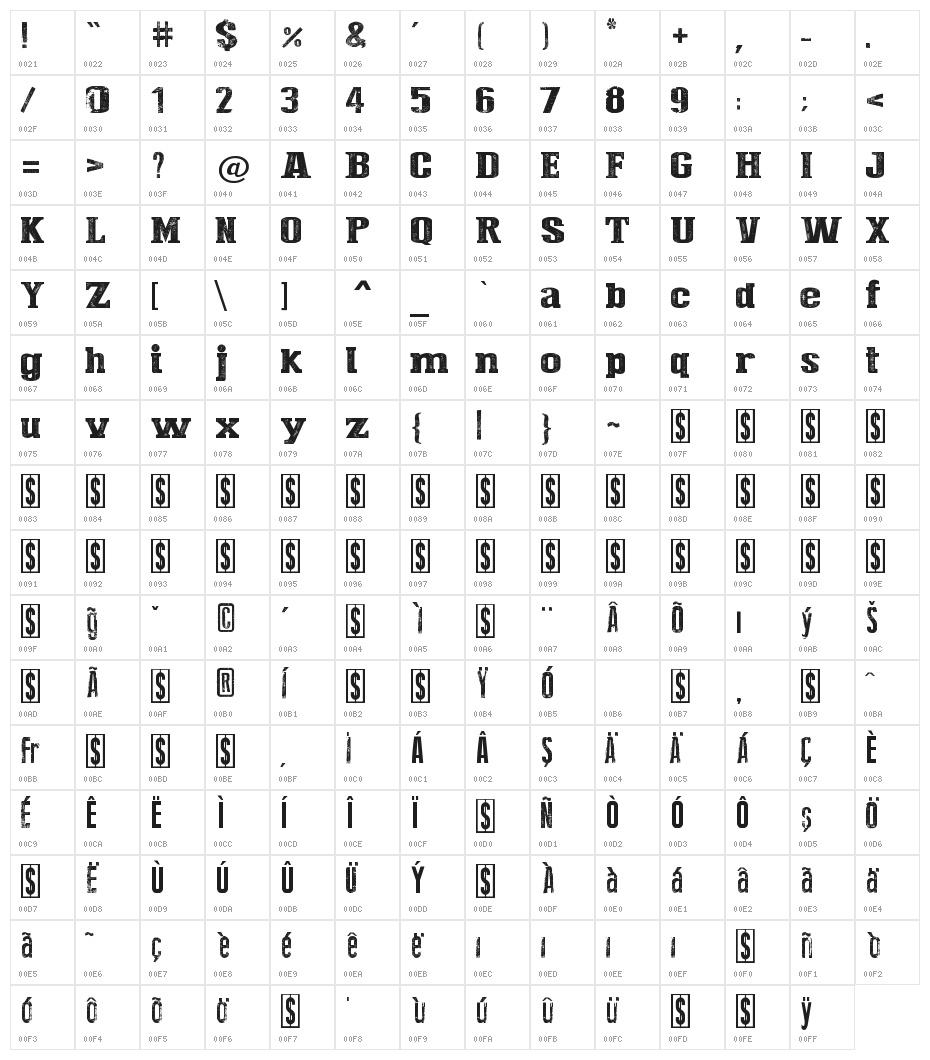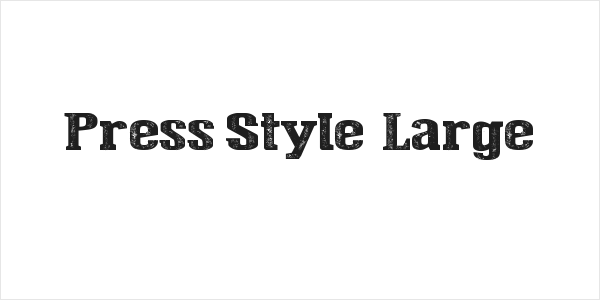
Press Style Large Font
✎ Distorted Eroded
| Projetos propostos | Ideal for posters, logos, branding, and any design requiring a vintage or industrial aesthetic. |